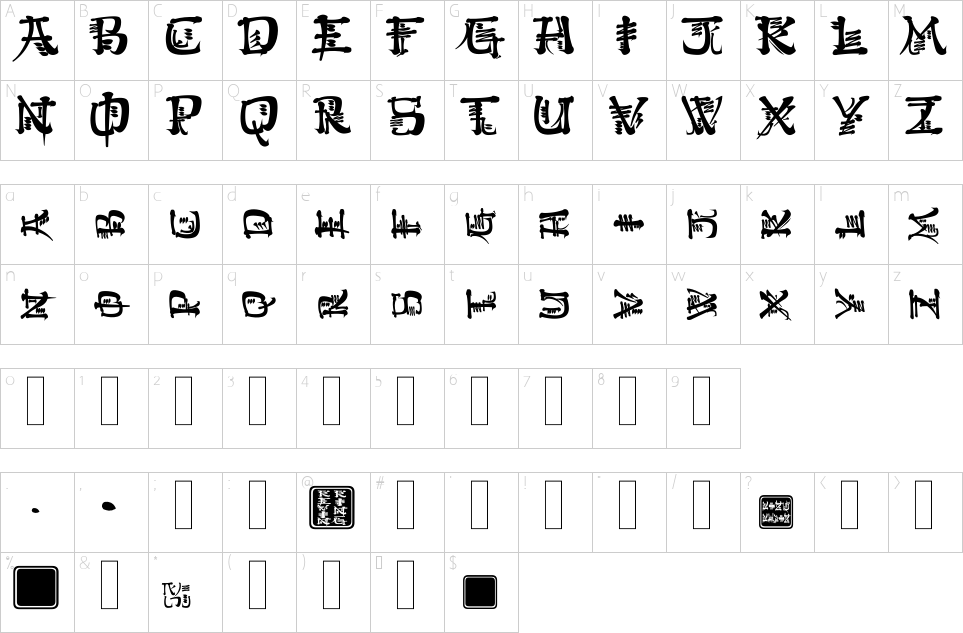
Descubra a sofistica e a originalidade do Kingthings Conundrum, uma fonte inovadora que enriquecerá seu design gráfico. Desenvolvida pelo King Things Fonts, essa fonte única e diversificada é ideal para criar títulos chamativos e letras de texto sofisticadas. Com suas linhas fluidas e nuances únicas, Kingthings Conundrum oferece a liberdade para explorar diferentes estilos, desde elegância clássica até uma linguagem futurista e ousada. Com a facilidade de uso para ambas as plataformas Windows e Mac, agora é fácil incluir esta fonte no seu trabalho. Com 18,242 downloads, o Kingthings Conundrum é uma escolha sólida para os criativos que desejam imprimir um toque único em suas obras. Descubra por si mesmo o poder desta fonte e revolucione suas criações com Kingthings Conundrum.